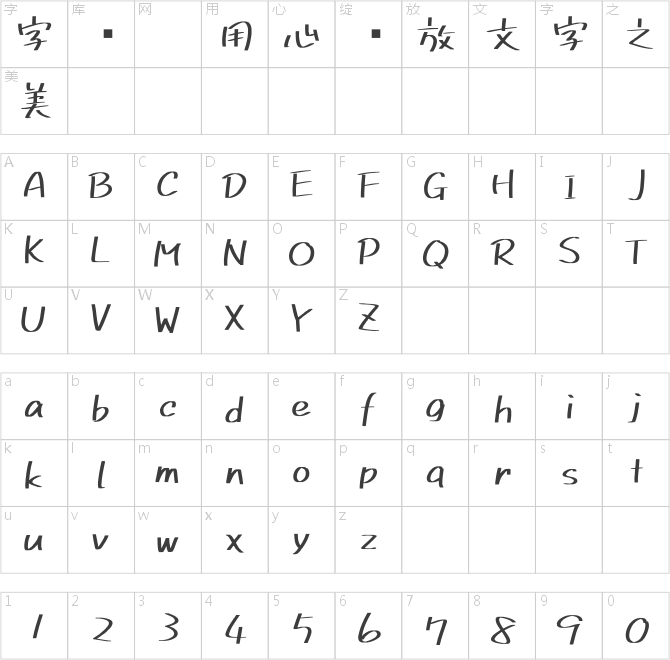
字体名称: 851麻花手写
851麻花手写
851麻花手写字体下载851MkPOP-851マカポップ
日本设计师851发布的免费可商用的字体
851麻花手写字体851MkPOP-851マカポップ字库是一款让人赏心悦目、百看不厌的日文字体,适合各类广告和产品包装设计应用,字体大小1.63MB,格式为ttf字体,上传用户是一直在守护,作者/版权方为851